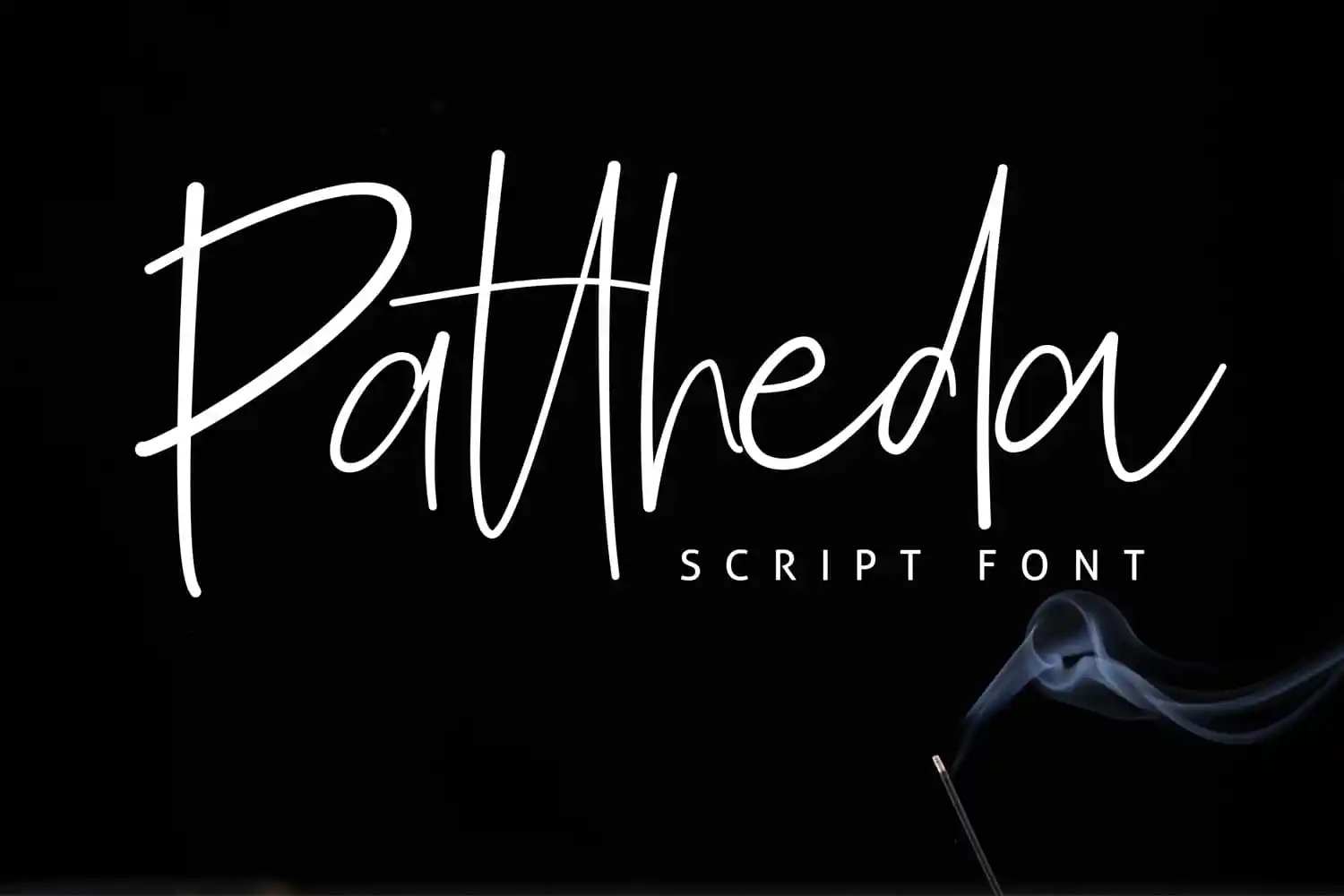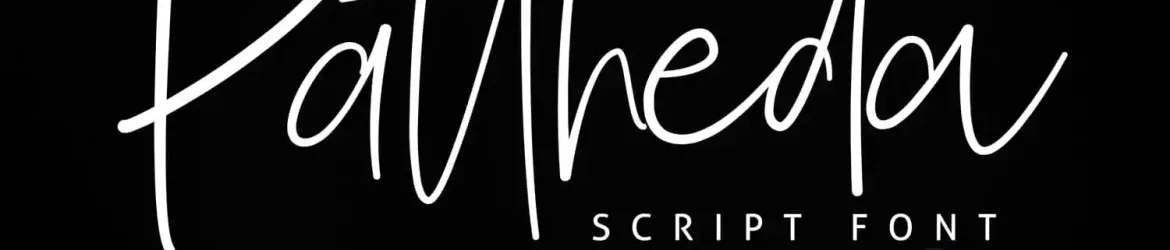
A Pattheda Script é uma nova adição à nossa vasta gama de fonts script disponíveis para download. Inspirada em materiais estilizados e lindos, essa font apresenta um visual moderno e incrível para seu próximo projeto. A font foi criada pelo AZCRTV Studio e possui um estilo de escrita natural, tornando-a uma escolha perfeita para design de panfletos, capas de revistas, cartões de negócios e mais. Com a Pattheda Script, você tem à mão uma ferramenta poderosa que pode transformar qualquer projeto em algo único e incrível. Seja ela usada em designs simples ou complexos, a font será sempre o ponto focal do seu trabalho. Experimente agora e descubra como esta font natural e elegante pode ajudá-lo a alcançar os melhores resultados para seus projetos gráficos. A Pattheda Script é uma ótima escolha para aqueles que valorizam tanto qualidade quanto beleza em suas criações.